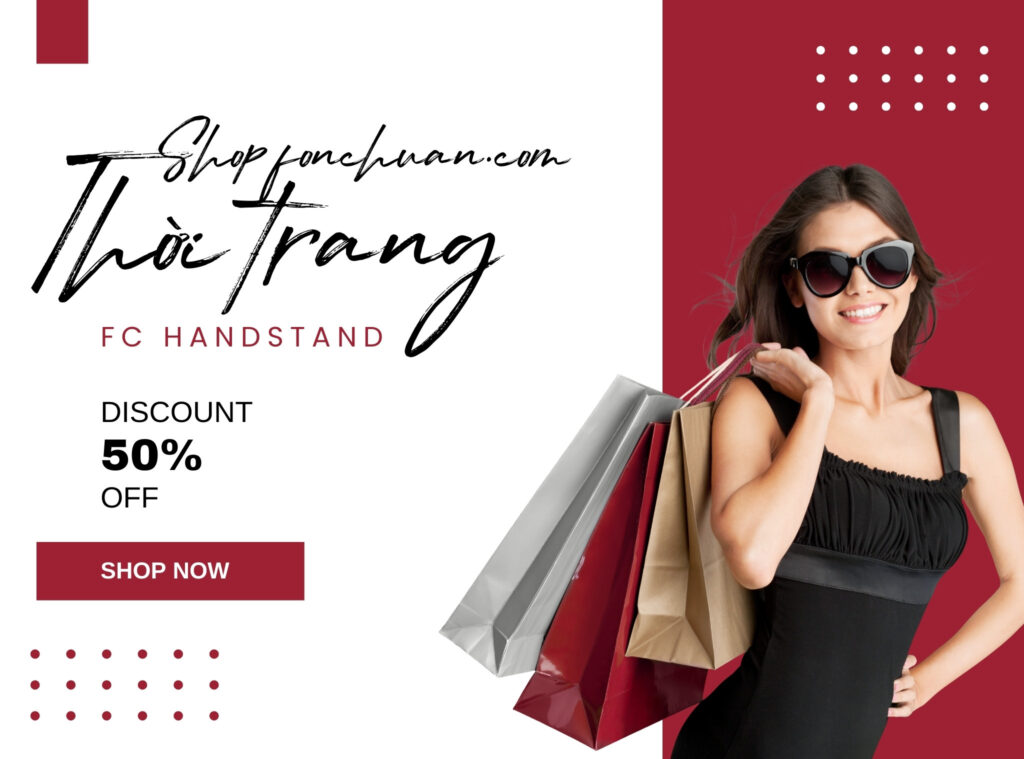
Font FC Handstand Việt Hóa
Handstand là một kiểu chữ viết tay nét độc đáo, được thiết kế bởi Areatype Studio. Font này mang phong cách brush hiện đại nhưng pha lẫn với phong cách thư pháp, với các nét vẽ tự nhiên và mạnh mẽ, tạo nên sự năng động và thu hút cho các dự án thiết kế.
Handstand mặc định hỗ trợ đa ngôn ngữ, bao gồm cả tiếng Việt nhưng chưa hoàn thiện, giúp nhà thiết kế tiếp cận đối tượng rộng rãi. Phiên bản Việt hóa FC Handstand được đội ngũ Font Chuẩn thực hiện chia sẻ miễn phí nhằm đáp ứng nhu cầu sử dụng tiếng Việt trong thiết kế, thay vì trả phí vip thành viên như cũng nơi khác. Thành viên của Font Chuẩn đã sưu tầm và chia sẻ font này, mang lại sự tiện lợi cho cộng đồng thiết kế Việt Nam.
Về thiết kế, Handstand sở hữu các đường nét tự nhiên, cấu trúc chữ cân đối và phong cách hiện đại, phù hợp cho nhiều mục đích sử dụng như thiết kế ngành thời trang, shop quần áo, poster và các ấn phẩm quảng cáo khác.